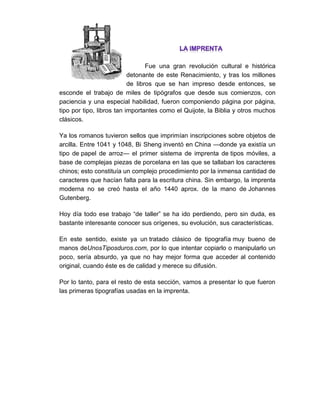
El termino tipografía se emplea para designar al estudio, diseño y clasificación de los tipos (letras) y las fuentes (familias de letras con características comunes), así como al diseño de caracteres unificados por propiedades visuales uniformes. De igual manera es el arte o técnica de reproducir la comunicación mediante la palabra impresa, transmitir con cierta habilidad, elegancia y eficacia. Por ello la evolución del diseño de las mismas responde a proyecciones tecnológicas y artísticas. El signo tipográfico se ha considerado como uno de los miembros más activos de los cambios culturales del hombre. Por otra parte, estos signos se combinan entre los primeros signos de escritura, cada signo nos expresa una idea, un concepto o una cosa; para comunicar ideas más complejas. Estos sistemas de escritura son los pictogramáticos, jeroglíficos e ideogramáticos. El campo tipográfico, abarca la realización de libros, periódicos, anuncios publicitarios, revistas, etc... Y cualquier otro documento impreso que se comunique con otros mediante palabras.
La primera escritura de la que se tienen registros surgió en la Mesopotamia en el año 4000 AC y fueron los sumerios quienes la idearon para identificar los productos en el comercio existente entre los ríos. Entre estos dos surgieron los Jeroglíficos egipcios (3100 AC) que fueron utilizados hasta el 394 AC. Los asiáticos inventaron la caligrafía, el papel y la imprenta. Todo esto venía forjándose desde el año 2000 AC; pero en ese entonces el oriente estaba totalmente aislado de occidente. La escritura cuneiforme, los jeroglíficos y la caligrafía china eran muy complejos, puesto que tenían cientos de caracteres. Para luchar contra esa dificultad surge el alfabeto, que es un conjunto de símbolos visuales (caracteres) que representan sonidos (habla). Los cientos de signos que existían se vieron reducidos a unos 20 o 30, lo cual era una verdadera revolución. El primer alfabeto fue el semítico del norte. Los cananeos, hebreos, fenicios se unen para buscar un sistema de escritura propio y común a todos. El alfabeto semítico del norte presento una notable influencia cuneiforme, proveniente de Creta y Egipto. De igual manera, en el occidente el alfabeto romano fue evolucionando y en el siglo X en el monasterio de St. Gall en Suiza, se desarrolló un nuevo tipo de letra comprimida y angulosa, la letra gótica, más rápida de escribir y que aprovechaba mejor el papel, factores importantes en un momento que la demanda de escritos se había incrementado notablemente, escritos que se realizaban a mano, primeramente en pergaminos y luego, a partir del año 1.100, en papel. La letra gótica se difundió por toda Europa, surgiendo diferentes variantes (Textura, Littera Moderna, Littera Antiqua, Minúscula de Niccoli, etc.).
La tipografía es una disciplina muy moderna, se calcula que la raza humana está presente en este planeta desde hace un millón de años, pero el hombre comenzó a escribir hace 6000, elaboró el primer alfabeto fonético hace menos de 4000 y desarrolló los primeros tipos móviles hace tan solo 200 años.
La evolución del ser humano está marcada por el fenómeno de la comunicación, uno de los mayores logros del hombre has ido el invento de un lenguaje y unas letras que le permiten expresar sus ideas, retenerlas y mostrarlas a los demás. Todas las formas de escritura encajan en una definición general y común: un sistema de comunicación humana que utiliza marcas visibles y convencionales relacionadas con el lenguaje hablado.
Los antecedentes de la tipografía están en la evolución de las palabras y las letras, también en las diversas manifestaciones escritas y su evolución hasta el alfabeto romano, precursor del alfabeto que ahora usamos.
La Tipografía tiene como fin principal crear, estilizar y dar estéticamente a las fuentes un atractivo visual, además de una utilidad determinada (por ejemplo la fuente Times para el periódico.) En paralelo al avance tecnológico, los diseñadores han podido hacer uso de la tecnología en pro de su oficio tipográfico. Tal desarrollo a la par permitió una evolución estilosa y práctica del tipo, facilitando el trabajo tanto del diseño como de la impresión en serie. El vocabulario usado para la descripción de las diferentes partes de una letra, se compone de una serie de términos acuñados desde hace mucho tiempo y que se asemejan a los usados para describir las partes de nuestro cuerpo. Así las letras tienen brazos, piernas, ojos, y otras partes como cola y hasta de las que afortunadamente nosotros carecemos (la mayoría). De todas formas, creemos que debido a las tradiciones del oficio en los diferentes países, no hemos visto todavía que la descripción de las partes de una letra coincida de forma unánime en los libros sobre tipografía y diseño. En todo caso, los términos que aquí se muestran constituyen un buen bajage para comprender y conocer las distintas partes de una letra, y han sido en cierta medida consensuados a partir de las fuentes consultadas. ÁPICE Unión de dos astas en la parte superior de la letra.
APÓFIGE Pequeño trazo curvo que enlaza el asta vertical con los terminales o remates. ASTA Rasgo principal de la letra que define su forma esencial. Sin ella, la letra no existiría. ASTA ASCENDENTE Asta de la letra que sobresale por encima de la altura de la X (ojo medio). ASTA DESCENDENTE Asta de la letra que queda por debajo de la línea de base.
ASTA ONDULADA O ESPINA Rasgo principal de la S o la s. PERFIL, FILETE O BARRA Línea horizontal entre verticales, diagonales o curvas. BRAZO Trazo horizontal o diagonal que surge de un asta vertical. BUCLE O PANZA Trazo curvo que encierra una contraforma.
COLA Prolongación inferior de algunos rasgos. CONTRAFORMA O CONTRAPUNZÓN Espacio interno de una letra total o parcialmente encerrado. CRUZ O TRAVESAÑO Trazo horizontal que cruza por algún punto del asta principal. CUELLO Trazo que une la cabeza con la cola de la g.
ESPOLÓN Extensión que articula la unión de un trazo curvo con otro recto. GOTA, LÁGRIMA O BOTÓN Final de un trazo que no termina en una gracia o remate, sino con una forma redondeada. HOMBRO O ARCO Trazo curvo que sale del asta principal de algunas letras sin acabar cerrándose. LAZO Trazo que une la curva con el asta principal.
OJAL Bucle creado en el descendente de la g de caja baja. OREJA Pequeño trazo situado en la cabeza de la g de caja baja. PATA Trazo diagonal que sirve de apoyo a algunas letras. También se puede llamar cola. SERIF, REMATE O GRACIA Trazo terminal de un asta, brazo o cola. Es un resalte ornamental que no es indispensable para la definición del carácter, habiendo alfabetos que carecen de ellos (sans serif).
UÑA O GANCHO Final de un trazo que no termina en remate, sino con una pequeña proyección de un trazo. VÉRTICE Punto exterior de encuentro entre dos trazos en la parte inferior de la letra.
Altura de las mayúsculas: Es la altura de las letras de caja alta. Altura X: Altura de las letras de caja baja, las letras minúsculas, excluyendo los ascendentes y los descendentes. Anillo: Es el asta curva cerrada que forman las letras "b, p y o". Ascendente: Asta que contiene la letra de caja baja y que sobresale por encima de la altura x, tales como las letras "b, d y k". Asta: Rasgo principal de la letra que la define como su forma o parte más esencial. Astas montantes: Son las astas principales u oblicuas de una letra, tales como la " L, B, V o A". Asta ondulada o espina: Es el rasgo principal de la letra "S" en mayúscula o "s" en minúscula. Asta transversal: Rasgo horizontal de las letras "A, H, f o t". Brazo: Parte terminal que se proyecta horizontalmente o hacia arriba y que no se encuentra incluida dentro del carácter, tal como se pronuncia en la letra " E, K y L". Cola: Asta oblicua colgante que forman algunas letras, tales como la " R o K ". Descendente: Asta de la letra de caja baja que se encuentra por debajo de la línea de base, como ocurre con la letra "p y g".
Inclinación: Ángulo de inclinación de un tipo. Línea base: La línea sobre la que se apoya la altura. Oreja: Es la terminación o terminal que se le añade a algunas letras tales como "g, o y r". Rebaba: Es el espacio que existe entre el carácter y el borde del mismo. Serif, remate o gracia: Es el trazo o termina de un asta, brazo o cola. He encontrado esta presentación que está muy interesante, sobre la clasificación de los
El abecedario latinofue una adaptación del alfabeto griego. Los griegos, que desde el siglo VIII a.C. se habían instalado en la Magna Grecia, entraron en contacto con los pueblos de Italia y les influyeron culturalmente, enseñándoles la escritura alfabética. Es importante saber que en la antigüedad no existían más que la mayúsculas o unciales, y que por tanto fueron las únicas que emplearon griegos y romanos. Probablemente la ciudad más influyente fue Cumas, cuyos habitantes pertenecían a los griegos occidentales, con un alfabeto algo diferente del griego jónico-ático. En época monárquica los etruscos dominan buena parte de la Península Itálica y aprenden de los griegos de Cumas la escritura, adaptándola a su lengua. Al final de la época monárquica, o al principio de la época republicana, los romanos adaptan ligeramente la escritura etrusca a su lengua. Después en época clásica, ante la enorme avalancha de helenismos que entran en latín, al abecedario se reajusta para poder representar los sonidos del griego -esta vez ya común- que eran extraños al latín. Las minúsculas empiezan a emplearse al final de la antigüedad y surgen de la necesidad de escribir el trazo completo de una letra sin levantar la mano del papel (o el material que fuere), redondeando los ángulos para conseguirlo. Como este proceso se produjo paralelamente en latín y griego después de muchos siglos de escritura independiente en ambas lenguas, el resultado de este proceso, las minúsculas, fue mucho más divergente que lo que había sido el de las mayúsculas.